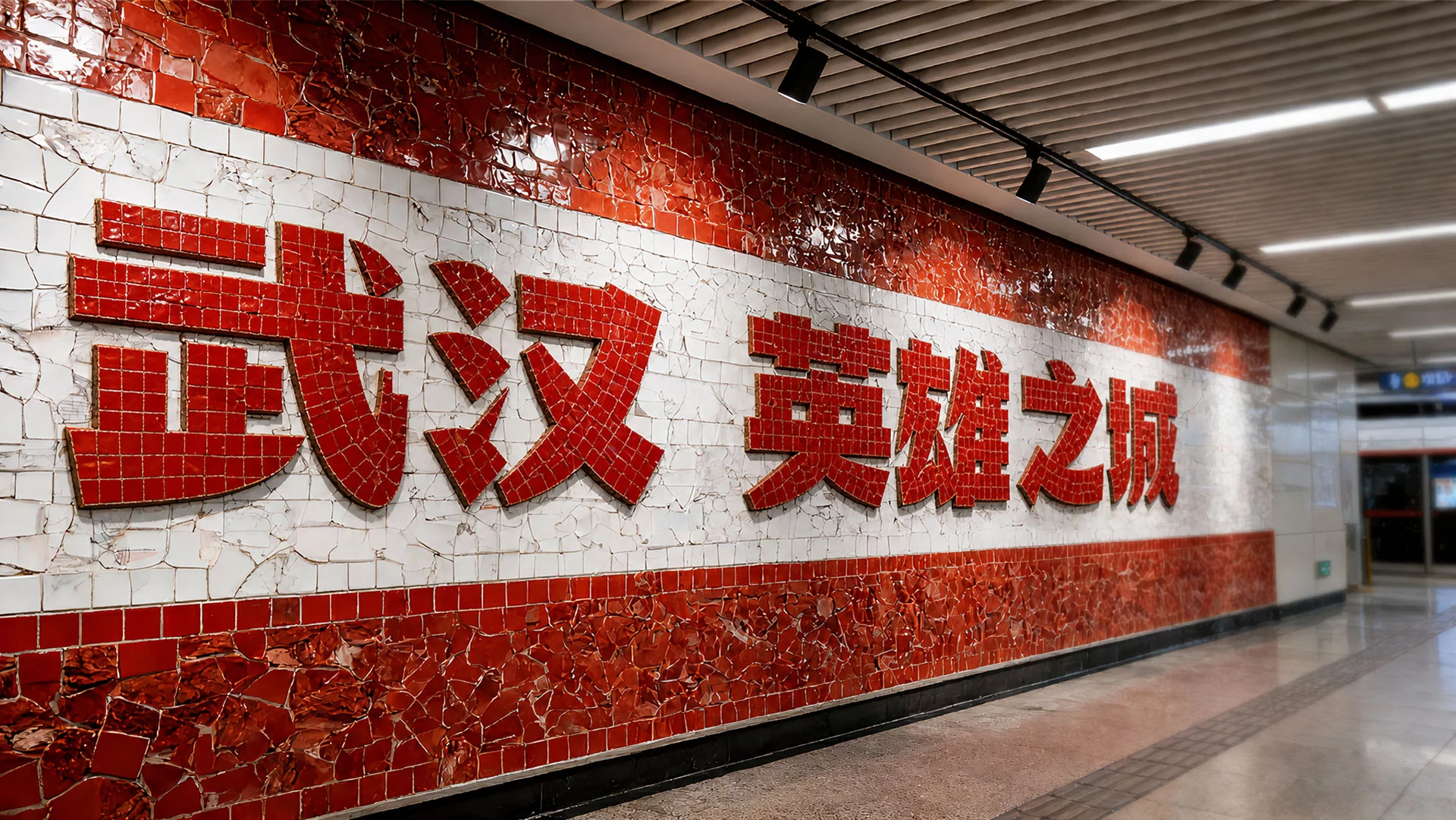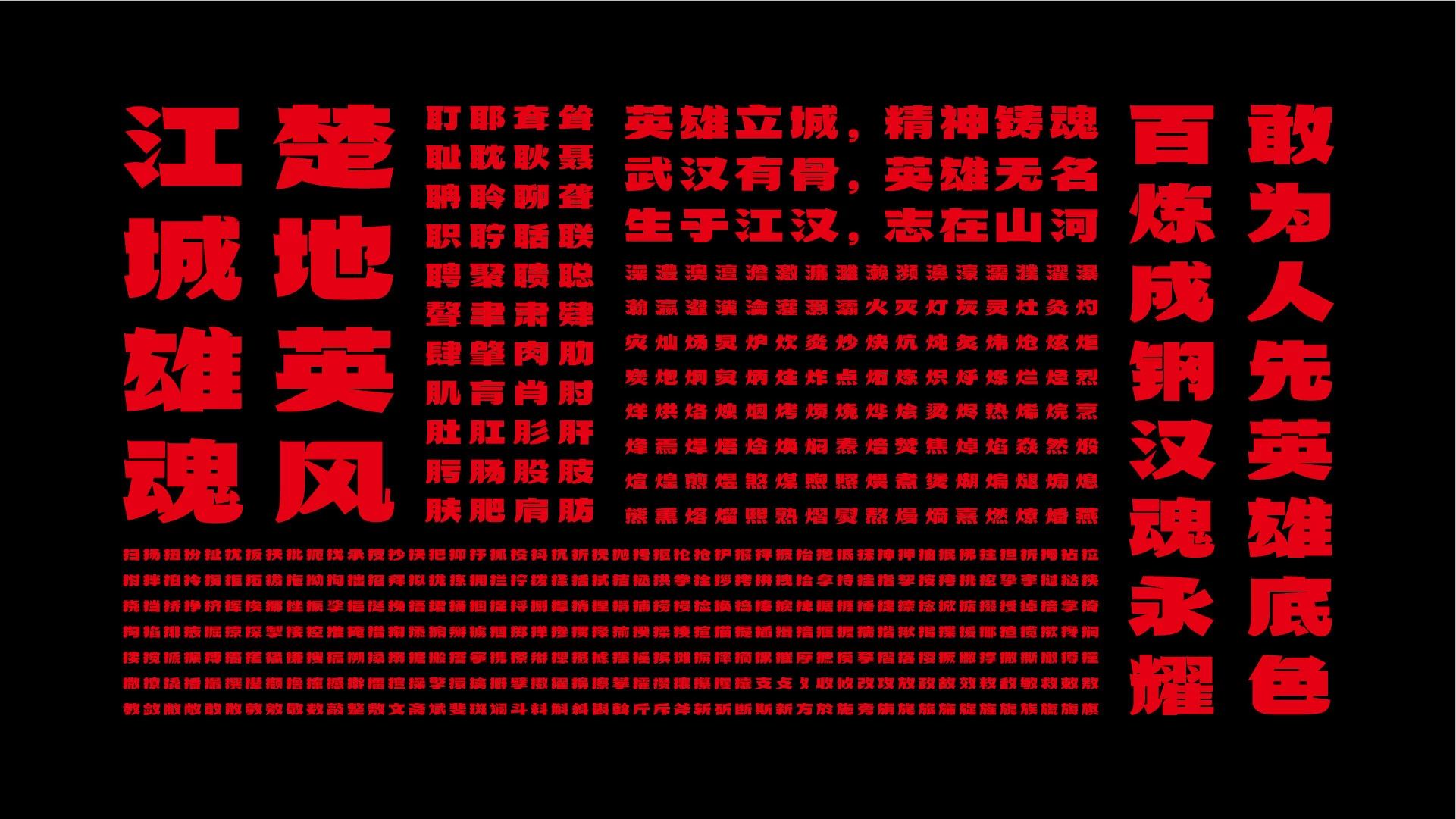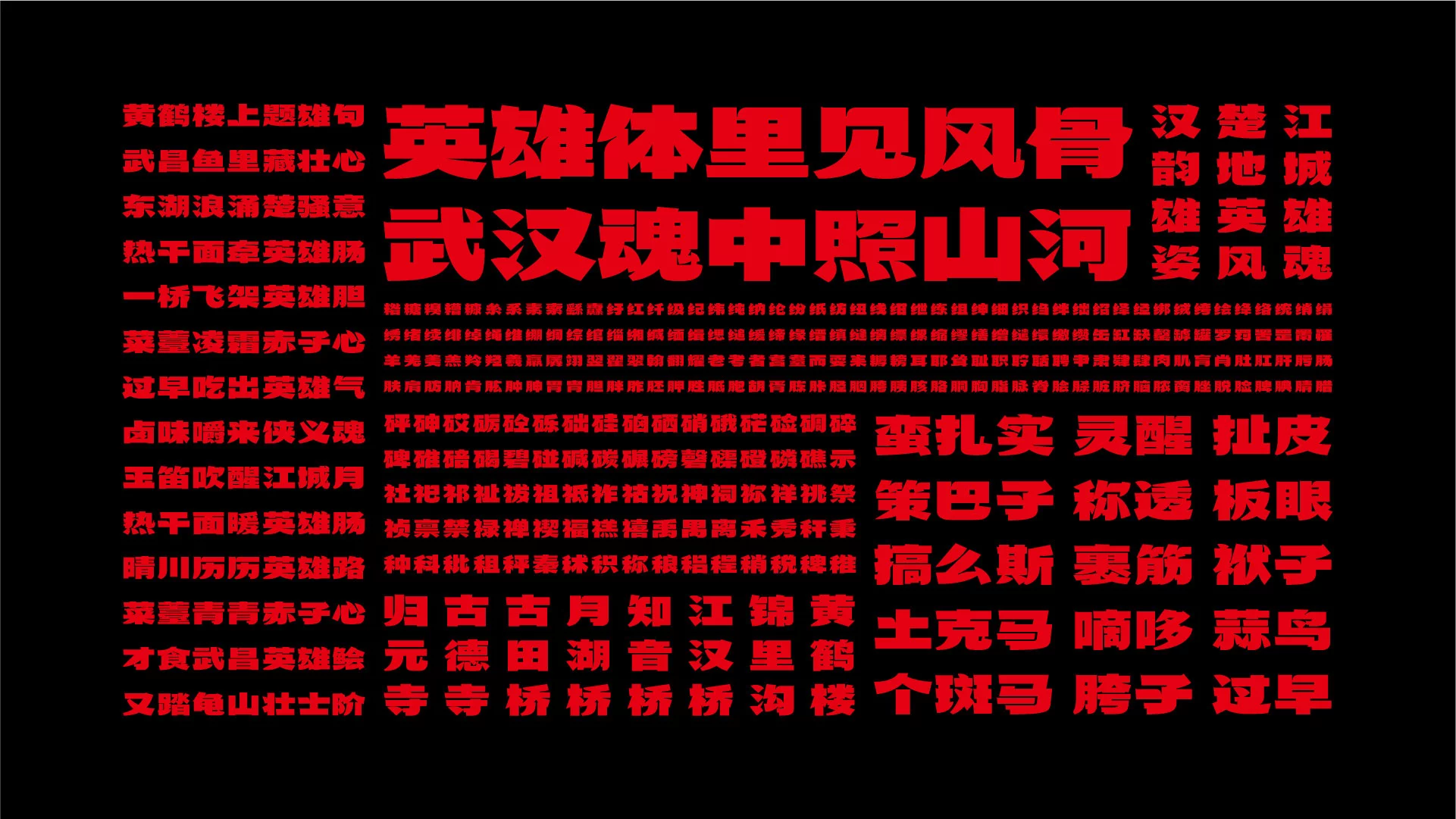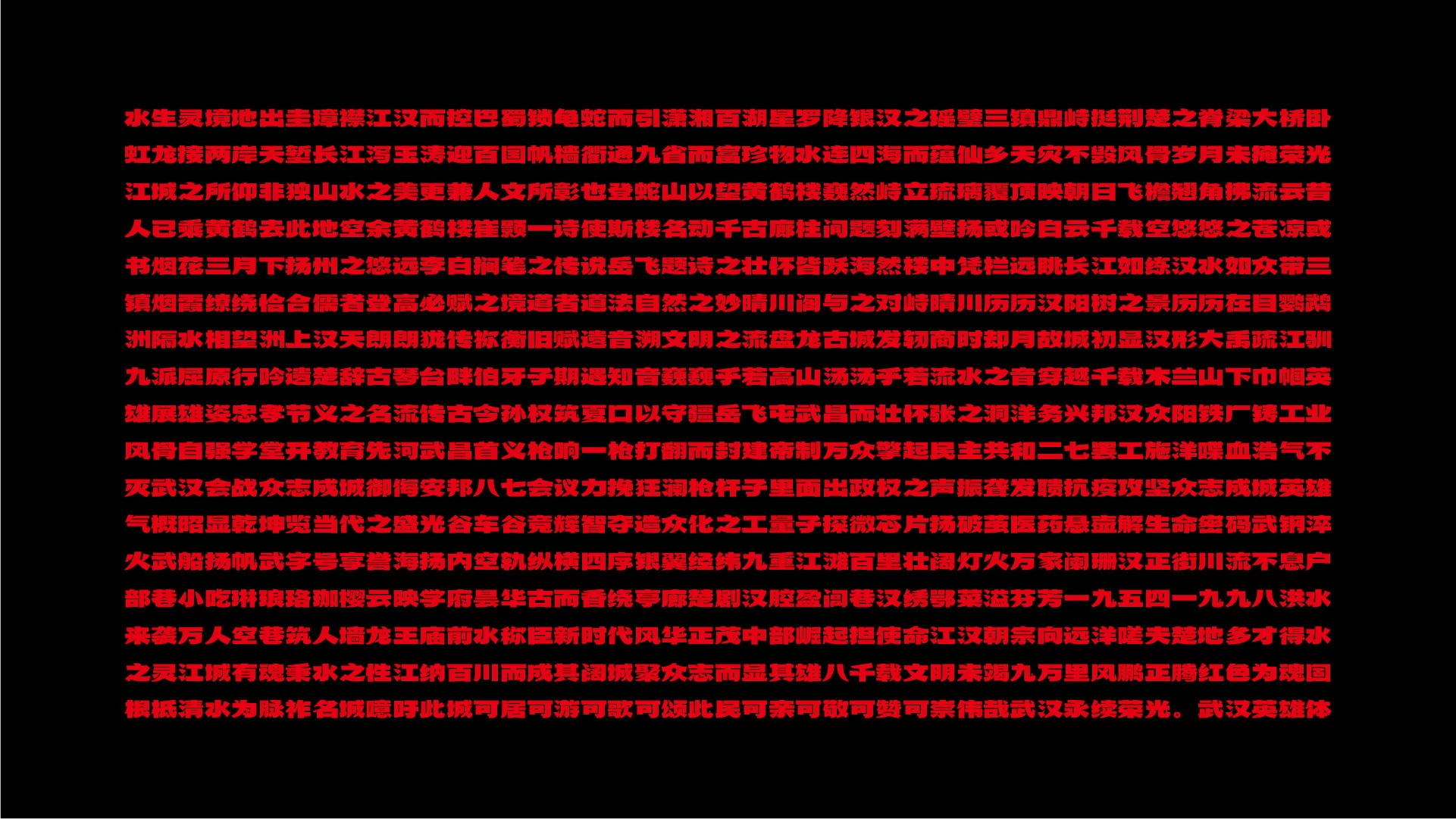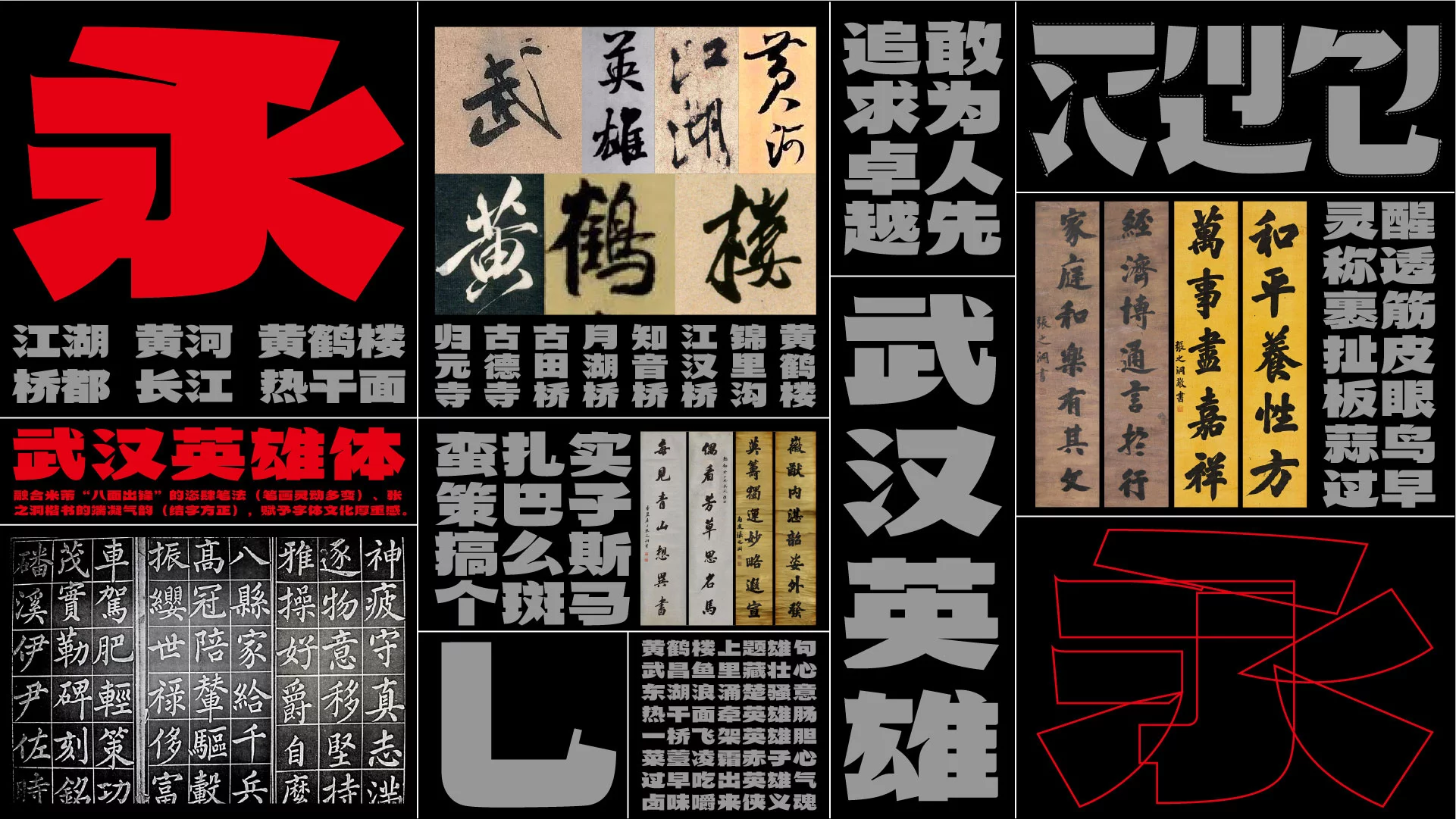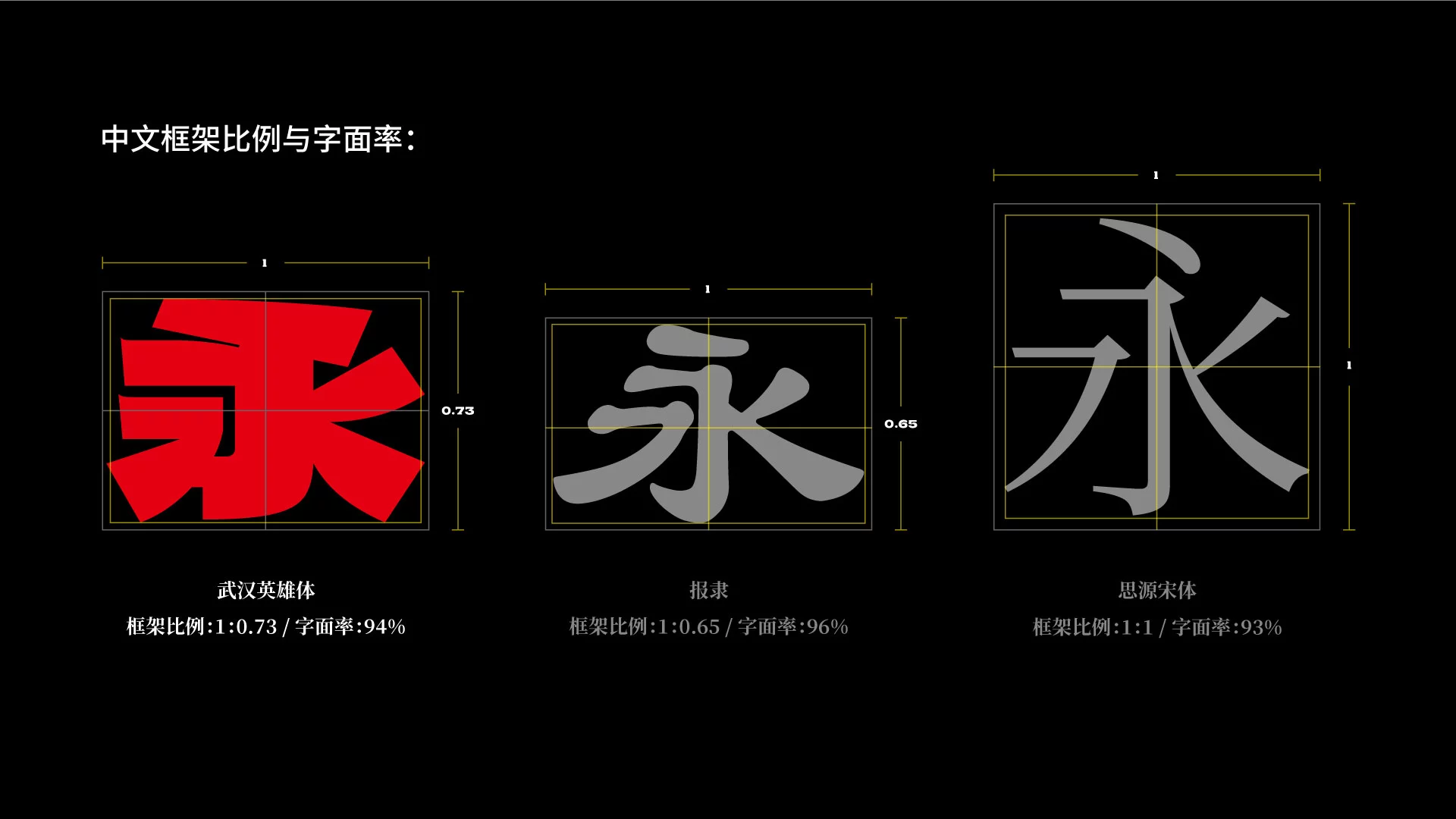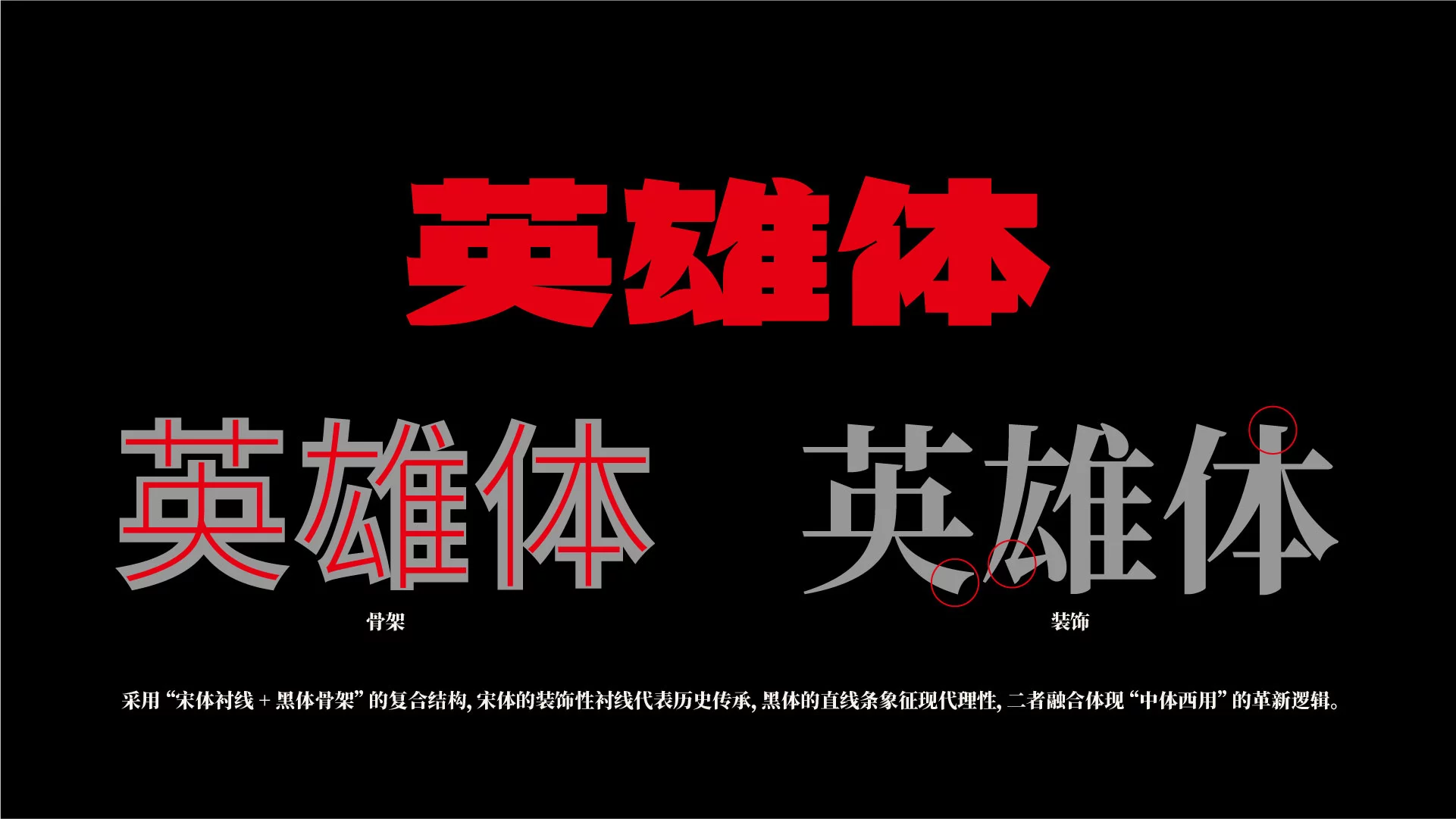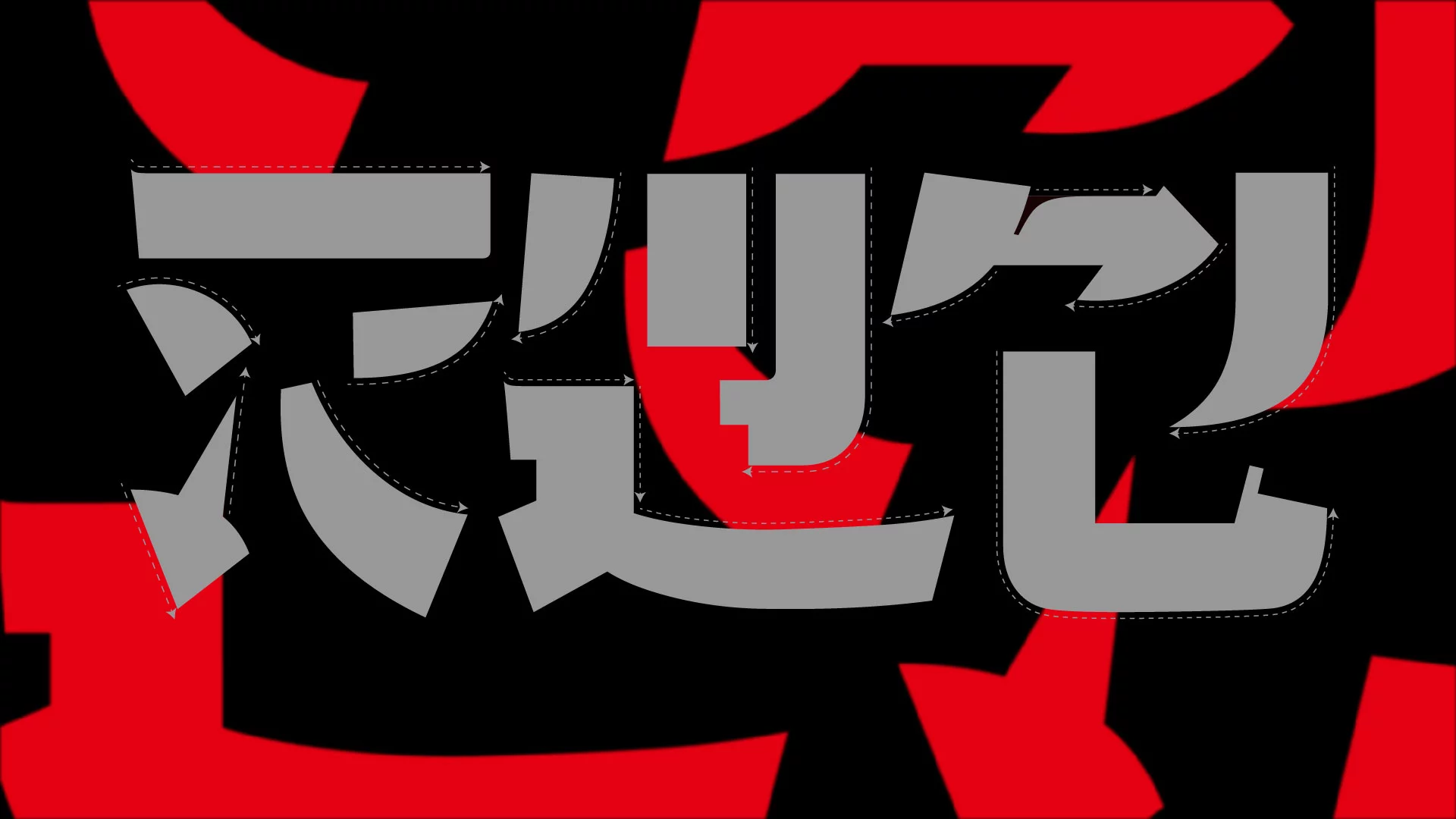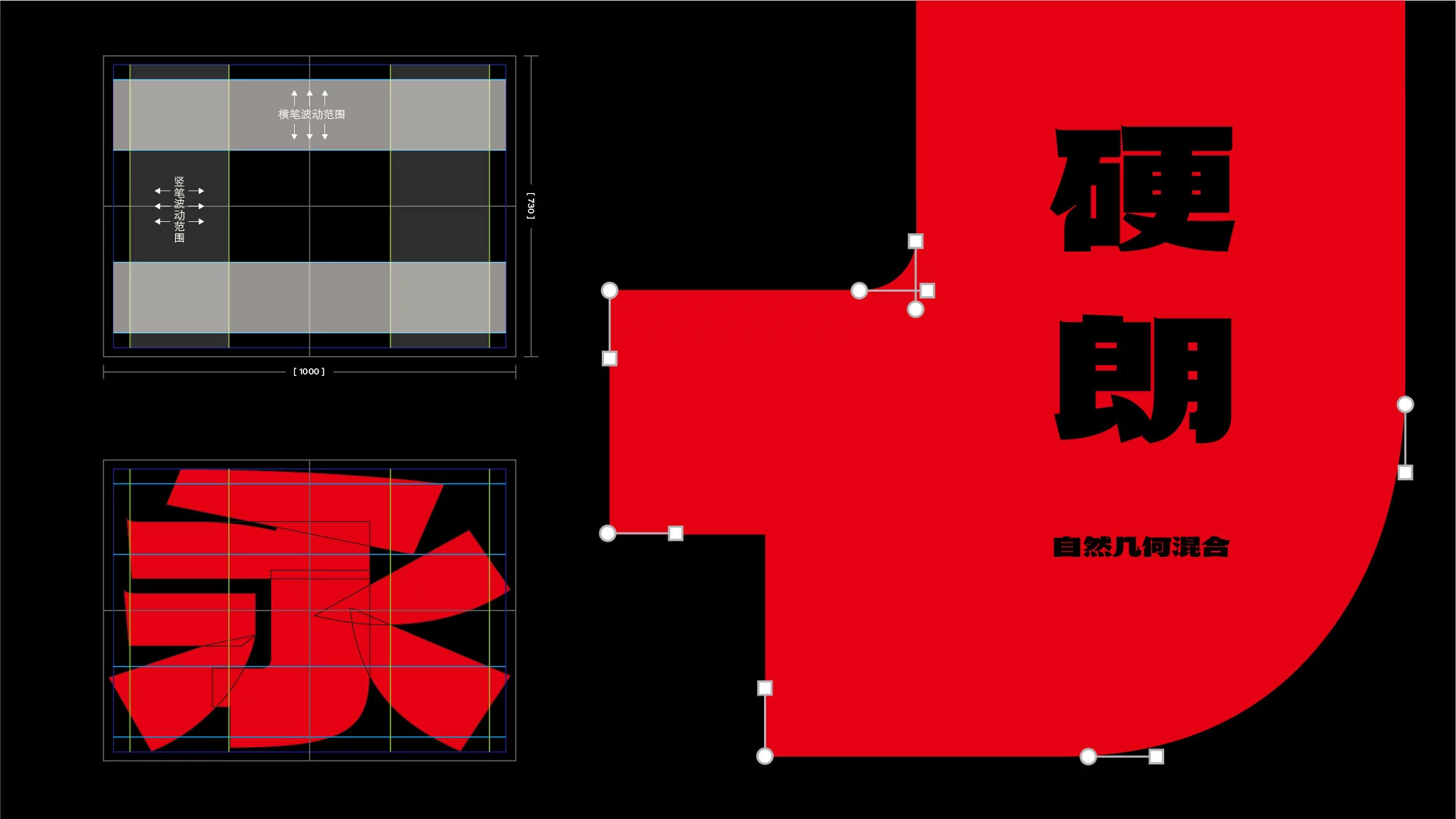
武汉英雄体
武汉英雄体(武漢英雄體、WuHanYingXiongTi)是武汉工商学院的徐郑冰教授,带领设计团队创作的一款免费商用中文字体。
当你在黄鹤楼下仰望飞檐、在长江大桥上望江潮入城,是否想过,这些属于武汉的画面,可以被浓缩到一笔一画之中?
今天就给大家介绍一款刚刚面世的宝藏字体:「武汉英雄体」
带着一股子荆楚大地的豪迈,把武汉这座城市3500年的历史底蕴,连同黄鹤楼的飞檐、长江大桥的桥墩,完完全全地刻进了汉字的骨血里。
「武汉英雄体」是一款融合了黑体与宋体精髓的实验性质标题美术字体。
在框架设定上,没有沿用常规字库1:1的正方形框架。而是从传统书法中汲取灵感,将字面设定得略微宽扁,中宫紧紧收窄,整个字体的重心向下沉,这使得字体更显稳重。
在整体结构上,借用了黑体的几何感,保证了视觉上的重量和力量,让字体方正与稳重。
但在笔画的形态上,又保留了宋体的特征,让字体更有文化韵味。
字体能明显感觉到方正分明、力透纸背的劲道。横、竖、折、钩,每一次出笔都有着极其丰富的韵律。
尤其是带钩的字尾设计,有着夸张的表现张力。
为了让字体在屏幕上也能完美呈现,在细节处做了干净利落的切角。又用圆角收边来缓和过分强硬的姿态,让刚与柔在方寸之间达到了平衡。
你看它的“捺”笔,起伏转折之间,是不是有点眼熟?
这个线条的灵感,直接来源于黄鹤楼舒展的飞檐。
把古建筑向上扬起的生命力,转化成了文字的收尾。
还有“武”字里极具张力的“戈钩”。
团队查阅了岳飞屯兵武昌的历史,把武将刚劲、开阔的风骨,揉进了这一笔的舒展之中。
再看“桥”字粗壮的竖画,上面稍微窄一点,下面稳稳地扎牢。
这个“上窄下宽”的收分造型,脱胎于武汉长江大桥的桥墩。把当年抗洪时坚不可摧的意志力,变成稳如泰山的视觉锚点。
在西文的适配里,采用了粗衬线的设计。在西文衬线字体里,这种风格有种独特的历史感、力量感,这和英雄体的气质也是很吻合的,算是很经典的搭配了。
不仅如此,武汉英雄体还支持拼字:
当这些带有城市印记的线条组合在一起时,整个字体既有着粗犷雄浑的力量感,又带着干脆利落的节奏感。
如果你来过武汉,你一定会对这座城市的气质印象深刻。
武汉从来都不缺大江大河的磅礴,更不缺“敢为人先,追求卓越”的硬汉骨气。
为了把这种精神具象化,武汉工商学院的徐郑冰教授,带着他的设计团队,开始了创作。
2024年,他们花了整整半年的时间采风。跑遍了起义门、江汉关这些历史坐标,钻进汉正街、兰陵菜市场,拍下了几十块带着岁月包浆的老招牌。
武汉英雄体完全脱胎于武汉的街头巷尾。
设计团队还在博物馆里死磕荆楚铭文和本土碑刻,跑到长江大桥、黄鹤楼、武钢去揣摩建筑的线条。
把城市里那些最接地气的视觉记忆一点点收集起来,抽丝剥茧,最终融进了这套字体的结构里。
在这套字库里,一共包含了6700多个汉字。没有AI的一键生成,没有套用现成的模板。
这里面每一个字,都是团队成员在电脑前,用鼠标一笔一划纯手工设计出来的。
据徐郑冰教授回忆,每个人每天撑死了也就只能完成10个字左右。整个团队足足耗时两年,才把这套字库打磨成型。
单单是字体基础框架,就推翻重来了12版。
作为核心灵魂的“武、汉、英、雄”这四个字,更是前前后后修改了上百遍。
其实熟悉徐教授团队的朋友可能知道,从2014年开始,他们就在做《字绘中国》项目,把全国45座城市的风景人文画进汉字里。
这次的「武汉英雄体」,正是他们将城市文化从艺术插画推向实用工具的一次蜕变。
「武汉英雄体」的文化感、力量感和沉稳大气的特质,我脑海里已经浮现出无数个激动人心的使用场景:
1. 文旅宣传与城市品牌。
如果你在做地域性较强的项目,比如景区推广、城市文化节、特产包装。
用英雄体做主标题,浓厚的文化底蕴瞬间就溢出屏幕了。
2. 热点事件与情绪海报。
需要传递坚定、勇敢、力量等强烈情绪时,武汉英雄体比常规黑体更有号召力。
3. 视频花字与影视片头。
宽扁的字形非常契合16:9的屏幕比例。
在短视频或者纪录片里,用来打出章节标题,复古又庄重的电影感立刻就能烘托出来。
文字,本身就是一种情绪的载体,是一座城市文化性格的缩影。
当你需要一种沉稳、力量、文化底蕴来支撑你的视觉表达时,可以放心地让「武汉英雄体」出场。
希望这份属于武汉的英雄气魄,也成为你作品里最打动人心的一笔!